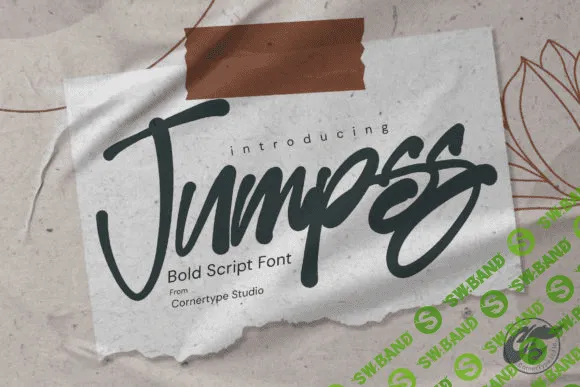
Название: Jumpss Font
[Creativefabrica] Jumpss Font
Jumpss - смелый шрифт, идеально подходящий для ваших логотипов, любимых проектов и т.д.
Он имеет вневременной стиль, и вы можете использовать его для создания эффектных дизайнов!